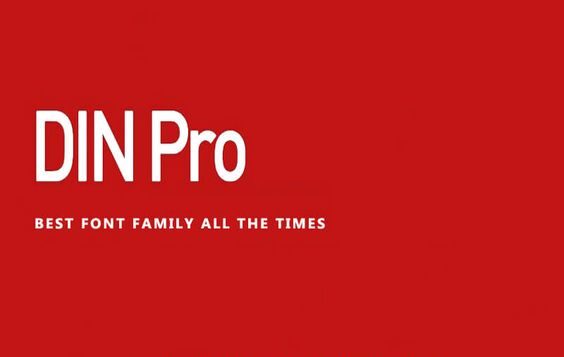
Dinpro Font Family
Dinpro Font Family là một bộ font chữ được yêu thích bởi tính chuyên nghiệp và linh hoạt.Font chữ được thiết kế với đường nét rõ ràng, hiện đại và dễ đọc thuộc bộ font chữ không chân vì thế mà Dinpro Font Family trở thành lựa chọn lý tưởng cho nhiều dự án thiết kế đồ họa, từ logo, tiêu đề cho đến các ứng dụng in ấn và kỹ thuật số. Với nhiều kiểu dáng và trọng lượng khác nhau, bộ font này mang lại sự đa dạng trong việc sáng tạo và đảm bảo tính thẩm mỹ cho các sản phẩm thiết kế. Dinpro Font Family không chỉ là công cụ mạnh mẽ cho các nhà thiết kế mà còn giúp tăng cường được sự chuyên nghiệp và tính nhận diện thương hiệu.